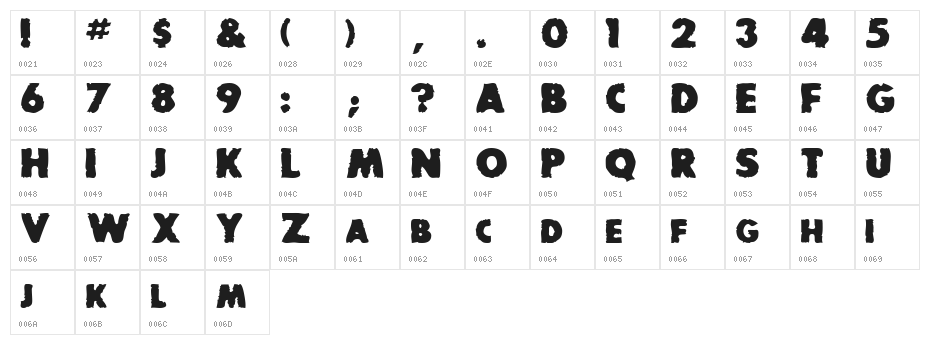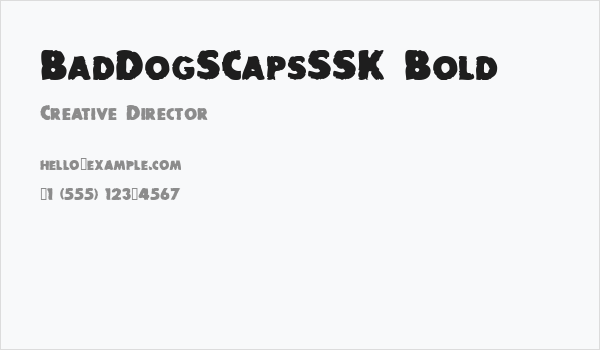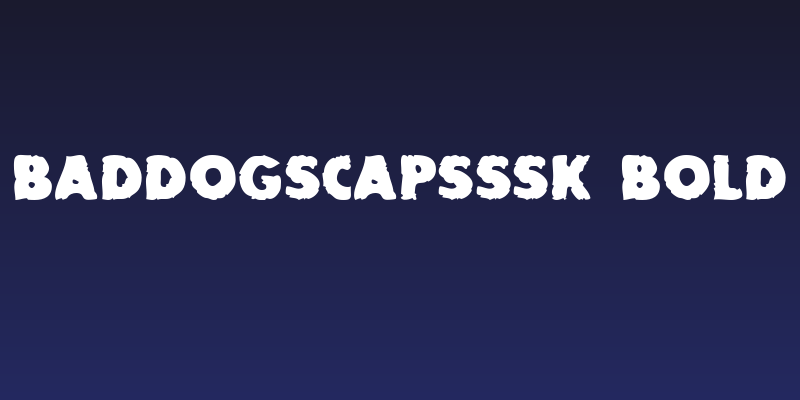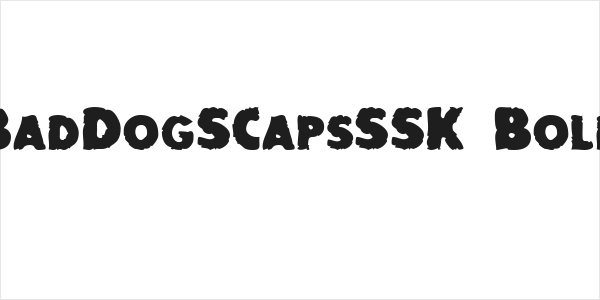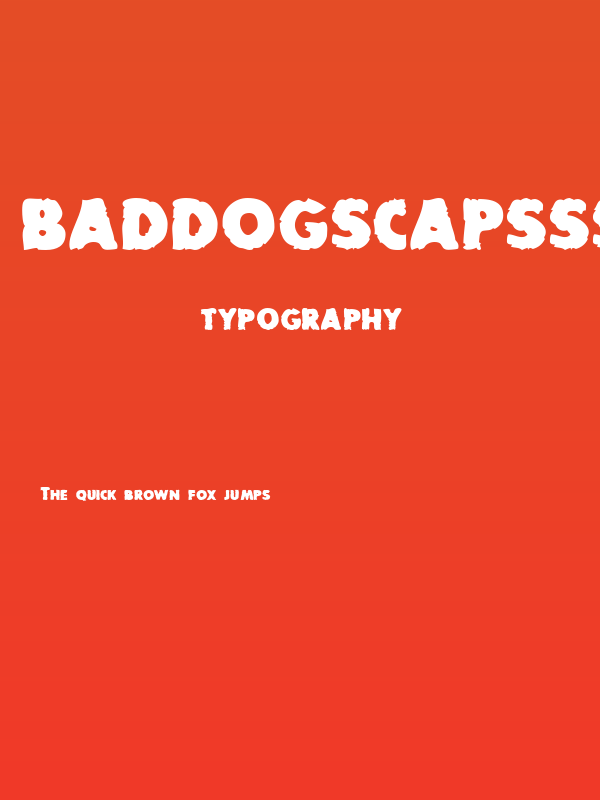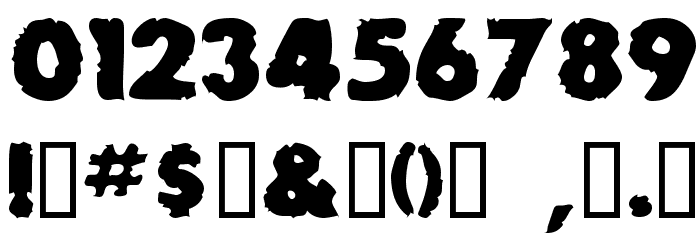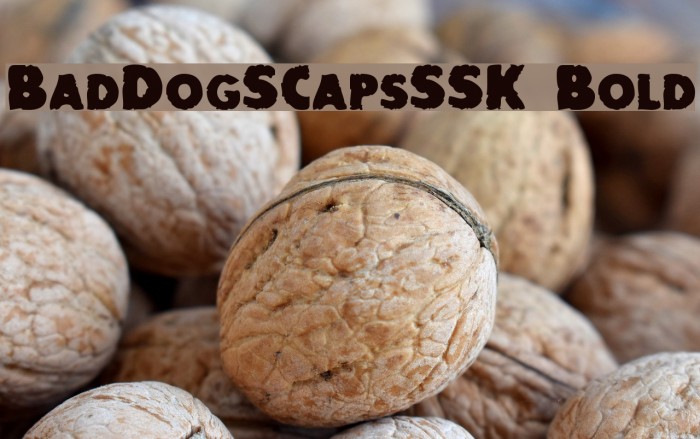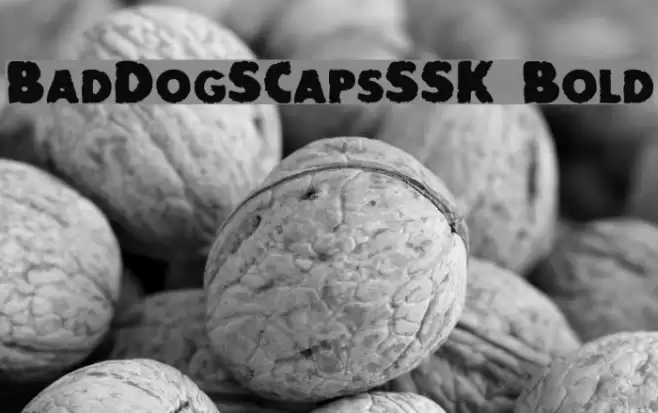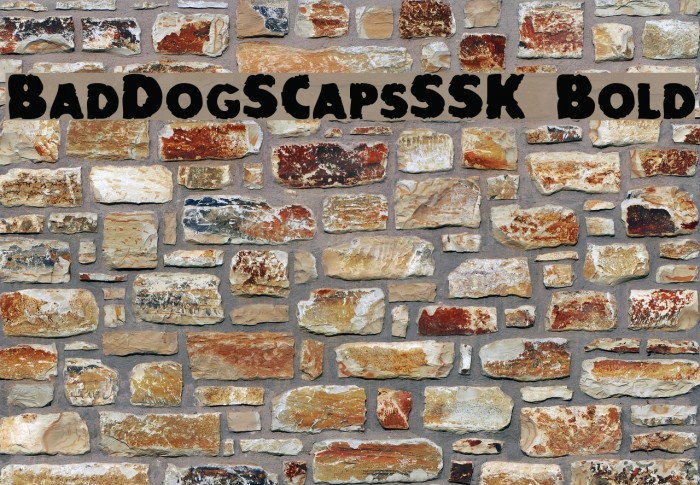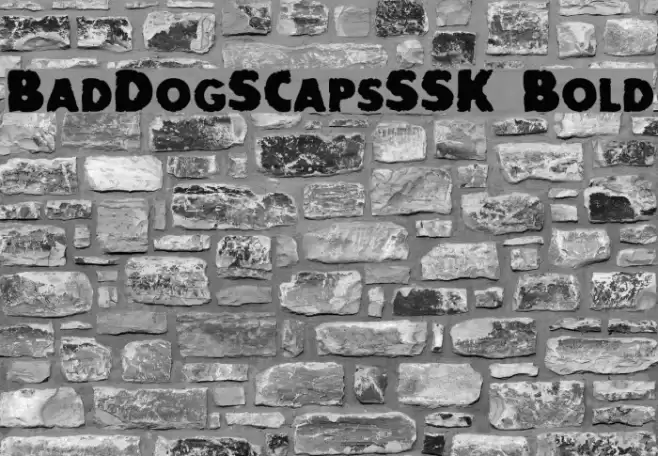
BadDogSCapsSSK Bold Font
| Рекомендуемые проекты | Ideal for posters, album covers, branding for edgy or alternative products, and any design needing a bold, impactful typeface. |